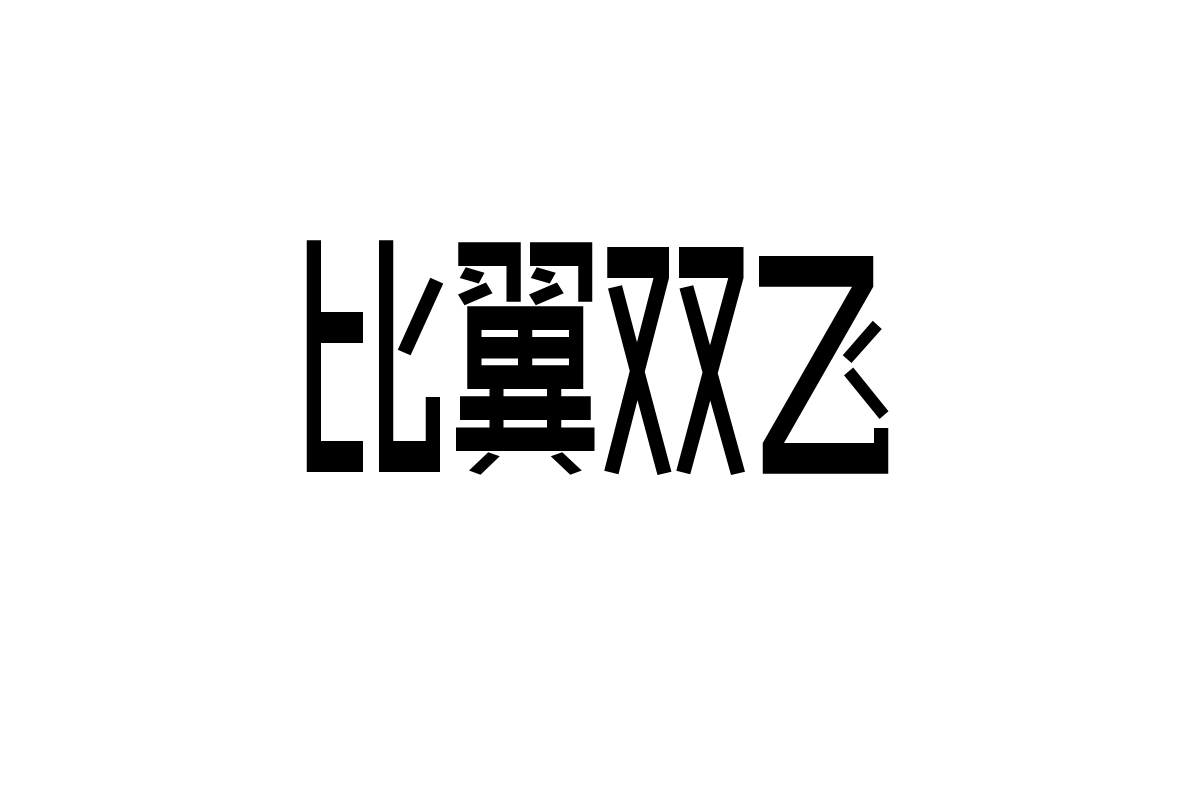
造字工房尚真体是一款现代中文字体,由造字工房设计。这款字体具有独特的风格和特点,包括:
1. 字形结构:尚真体的字形结构简洁明了,线条流畅自然,给人一种清晰、易读的感觉。
2. 笔画处理:尚真体的笔画处理精细,每个笔画都经过精心设计,使得字体看起来更加美观。
3. 风格特点:尚真体具有一种现代感和艺术性,适合用于广告、设计、包装等需要强调视觉效果的场合。
4. 适用范围:尚真体适用于各种类型的文本,如标题、正文、装饰文字等。
总体来说,造字工房尚真体是一款具有独特风格和特点的现代中文字体,适合用于需要强调视觉效果的场合。